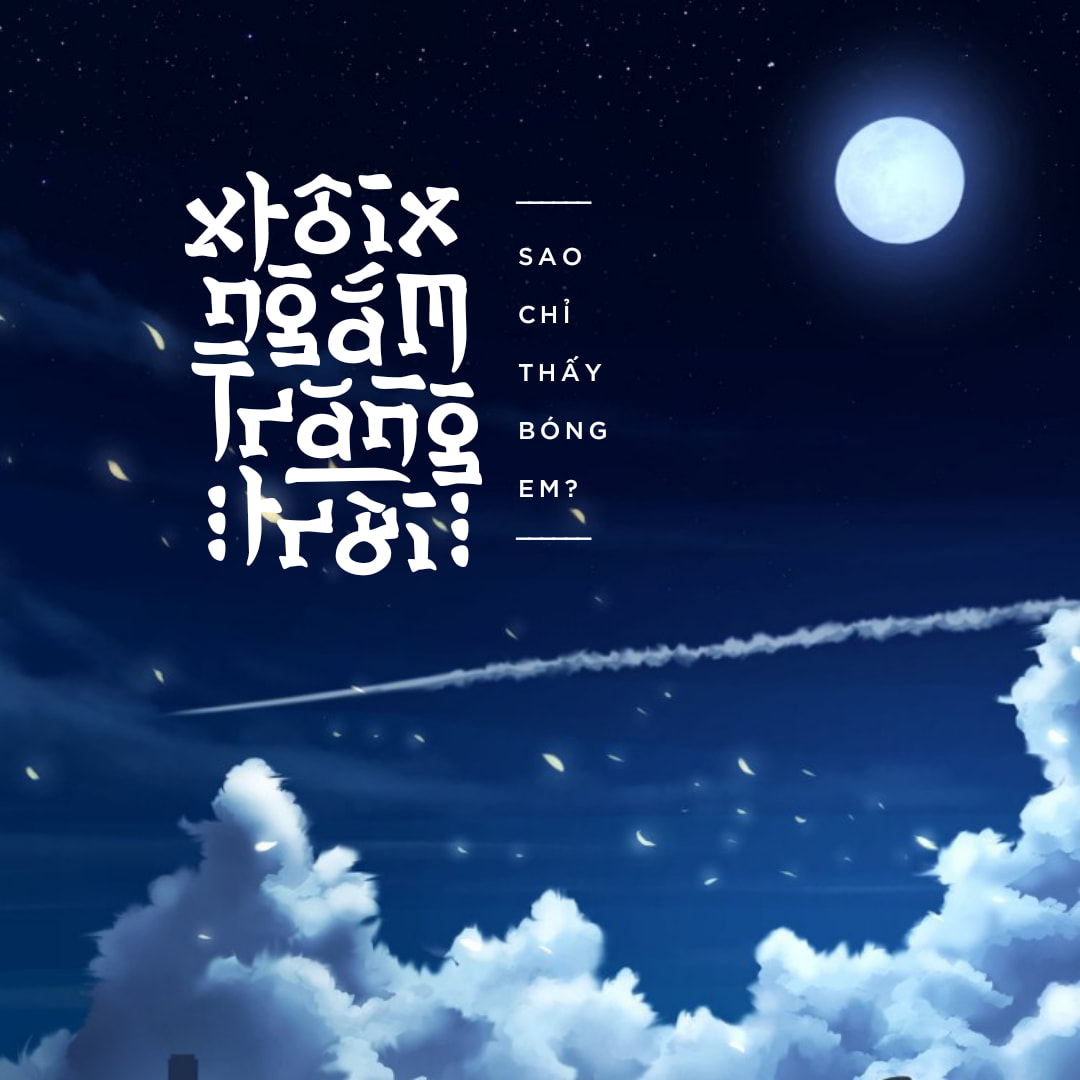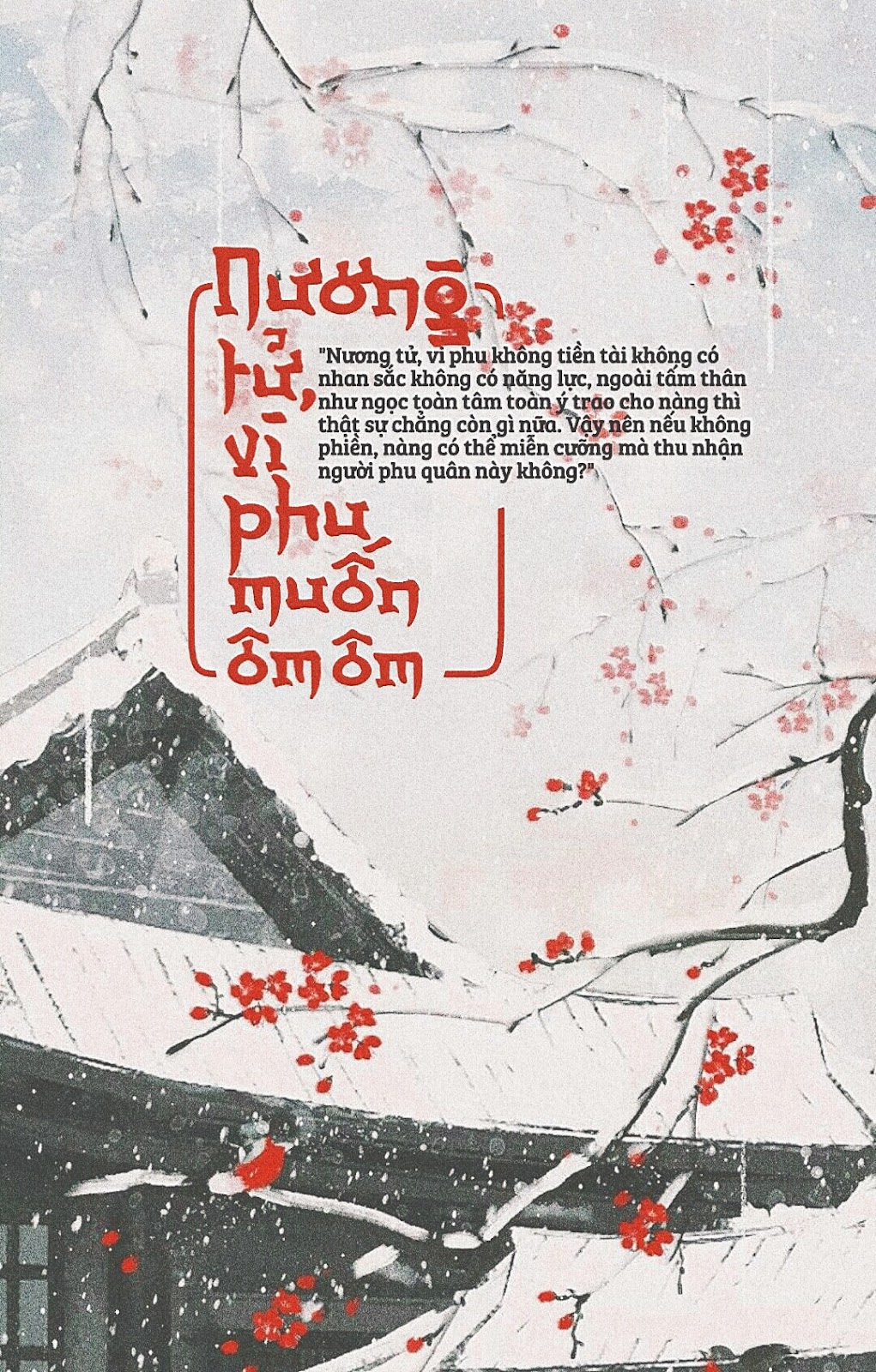
Font việt hóa A Annyeong Haseyo siêu xinh
Font việt hóa A Annyeong Haseyo là một font chữ lấy cảm hứng từ các ký tự Hàn Quốc với các ký tự đẹp và cân đối khá phù hợp để sử dụng trong các thiết kế như cổ trang, thư pháp, bìa truyện… Cre: LNTH